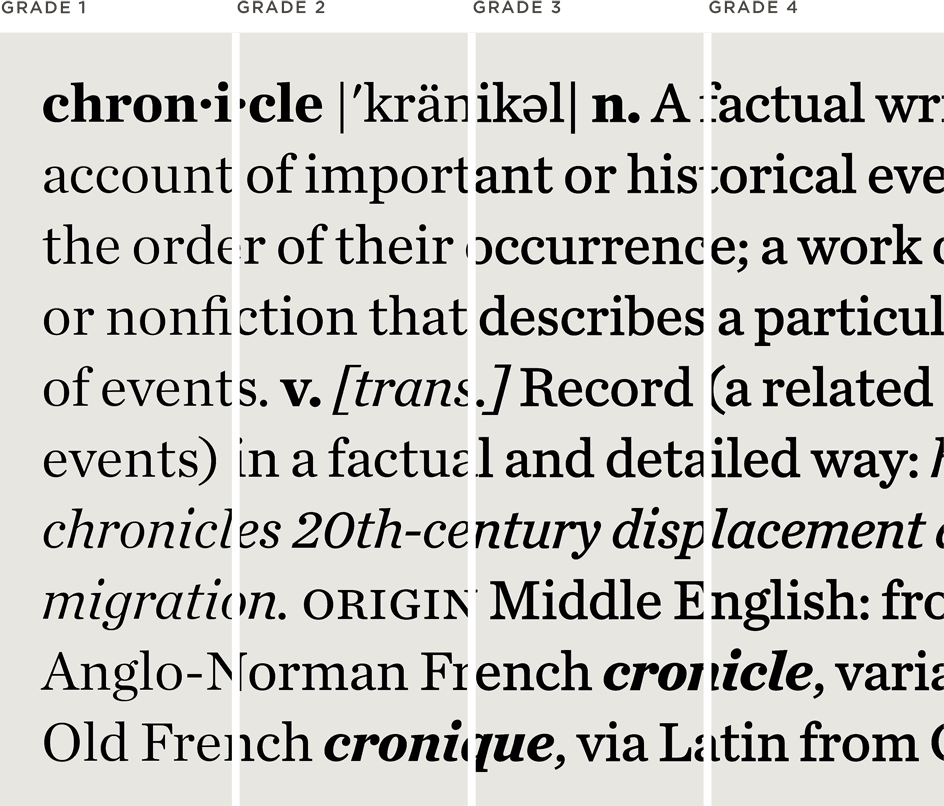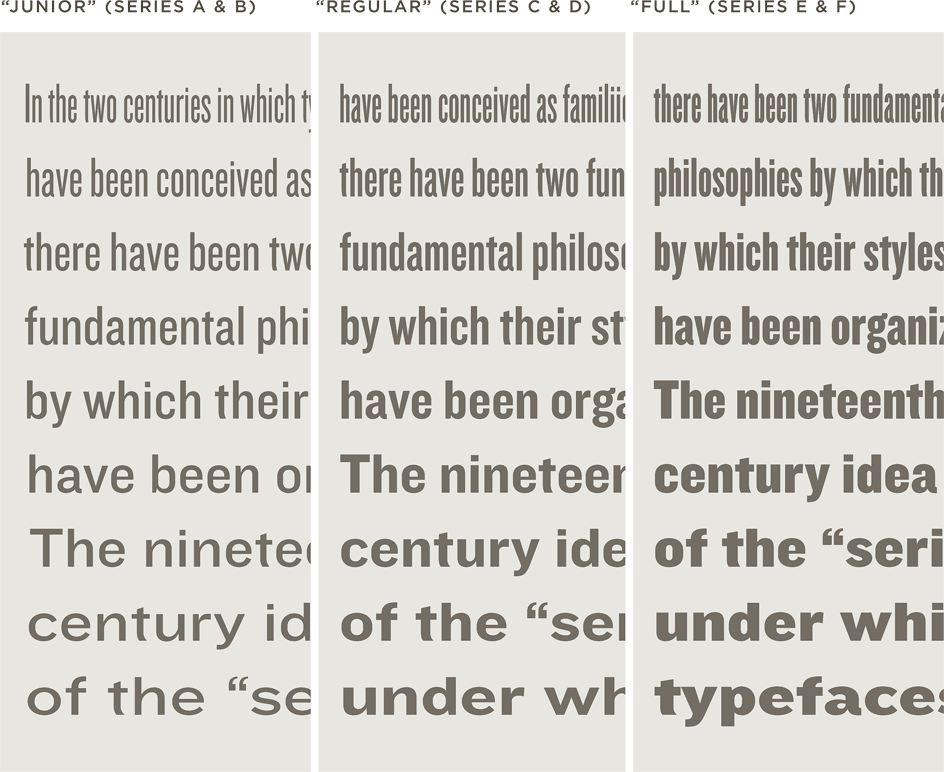
Welche Serifenschrift mit Knockout oder Heroic Condensed?
ich suche eine gut leserliche, passende Serifenschrift für Fließtext als Kombination zu einer schmal-und hochlaufenden Grotesk , wie der Knockout oder Heroic Condensed.
Also Headlines werden größtenteils in der Grotesk gesetzt. Hab mich noch nicht entschieden, aber oben genannte kommen in Frage. Als platzsparende Serifenschrift fiele mir die Chronicle Text ein, aber so ganz zufrieden bin ich nicht. Findet ihr, die Lyon passt dazu? :-/
Habt ihr vielleicht Vorschläge für eine möglichst nicht zu altbackene Serifenschrift?
Ganz toll wäre es, wenn sie nicht nur im Fließtext funktioniert, sondern auch als Displayfont einzusetzen ist, um z.B. mal Zitate groß zu machen?
Einen barock-klassizistischen Anstrich finde ich eigentlich schon mal gar nicht so unpassend zur Knockout/Heroic. Da ginge auch Utopia, Melior, Kepler usw. Ist aber alles nicht der neuste Schrei.
FF Quixo, Ingeborg, FF Cellini … wären da sicher frischer und auch schön displaytauglich, aber für allzu lange Texte wahrscheinlich schon etwas anstrengend. Könnte mir daher vorstellen, mit der Richler einen interessanten Mittelweg zu finden.
Kannst Du uns noch ein paar Details (Umfang/Thema/…) verraten? Dann müssen wir nicht so ins Blaue schießen. ;-)
Danke, aber die Marat ist mir ein bisschen zu speziell.
Danke für die vielen Vorschläge! Die Ingeborg gefällt mir ganz gut. Die hab ich auch. Muss mal gleich ausprobieren, wie die sich im Fließtext macht. Der Fließtext ist schon wichtig, da damit Interviews und längere Texte gesetzt werden.
Es geht übrigens um einen Magazinentwurf im Bereich Kultur/Lifestyle.
Dann könnten Dich auch Acta, Harriet oder Abril interessieren.
Wobei ich auch die Alda nicht schlecht finde, die hat aber keine extra Displayschnitte.